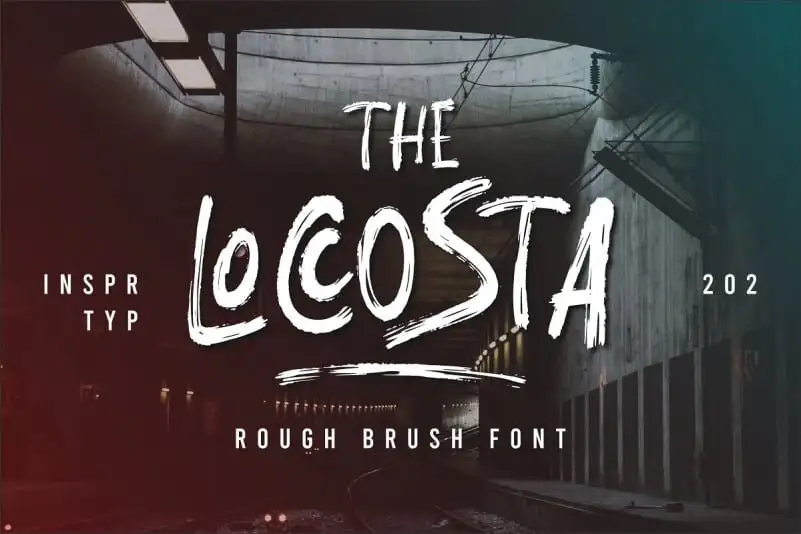
The Loccosta Brush Font – Download Grátis
Introduzimos The Loccosta Brush Font, uma fonte script criada por 99designs. Esta fonte é uma obra-prima do desenho a mão livre que foi projetada com um pincel seco, resultando em texto com toque refinado e personalizado. A fonte é perfeitamente adequada para uso em aplicações como logotipos, identidades de papelaria, cartazes, design de roupas, selos ou qualquer outro projeto que exigir uma personalização exuberante. O The Loccosta Brush Font oferece todas as letras maiúsculas e minúsculas, números, sinais de pontuação e inúmeros recursos variáveis por caractere. Inclui alternativas OpenType, ligaturas comuns e até mesmo swashes adicionais para que você possa personalizar suas próprias criações. Este é um recurso perfeito para qualquer tipo de projeto visual – desde logotipos a selos de embalagem, passando por identidades de papelaria e cartazes. O The Loccosta Brush Font não apenas oferece beleza e versatilidade em seu design único, mas também permite uma personalização intensiva que pode adicionar um toque especial aos seus projetos. Foi pensado para atender a um vasto espectro de usos, garantindo que você tenha o recurso perfeito para manter suas criações únicas e inovadoras.